Bordul diferență și o cratimă, tipografie
Cratima (diviz veche de ea Divis - .. Conectarea semn diviziune semn, de la Divisio latină -. (Time) diviziune) minusuri - ortografia non-alfabetice semna alte sisteme de scriere rusă și multe, care separă cuvintele. liniuță bord scurt grafic.
Dash (tiret francez de tirer - .. Stretching) - unul dintre semnele de punctuație. utilizat în mai multe limbi. Rusă alfabet Bordul a introdus scriitor și istoric N. M. Karamzin. Anvelope este medie (este, de asemenea numit scurt) și lung.
- liniuþe scurte este numită și „en-liniuță», «n-liniuță», deoarece lungimea sa este egală cu lățimea litera N. scurtă liniuță este plasată între numere, de exemplu, 5-10. În acest caz, cratimele scurte nu se luptă în afara spațiului.
- Em bord este numit și „em-liniuță», «m-cratimă», pentru că lungimea sa este egală cu lățimea literei M). Em Dash este o liniuță. Acesta este plasat între cuvintele la nivel sintactic, și din cuvintele din jur separate prin spații, adică, ea împărtășește parte a tezei: .. Subiectul și predicat, care este un substantiv în cazul nominativ. Linie lungă reprezintă o pauză lungă în propoziție. De exemplu, „Dash - un semn de punctuație.“ De asemenea, cratima este utilizat în propoziții incomplete, atunci când nu există nici un predicat sau ambele propoziției principale. De exemplu, „Deasupra capului - un cer fără nori.“ Cu cratimă exprima intonație specifice. Em cratimă este utilizat în vorbire directă.
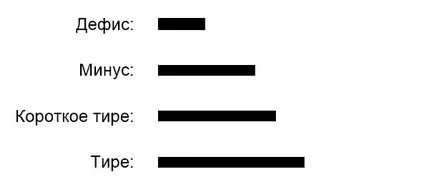
Utilizarea liniuțele și cratime sunt ușor de reținut, dacă vă apucați principiul: anvelope - o linie lungă, care este de obicei folosit într-o propoziție, nu un cuvânt. Cratima - caracteristica scurt, care este de obicei folosit într-un singur cuvânt.